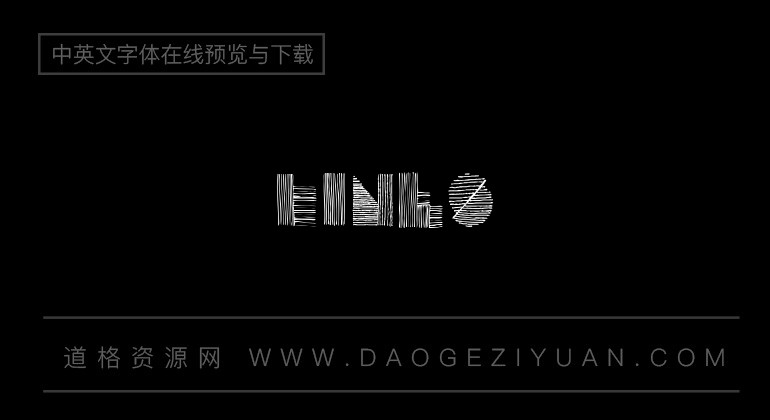
Lines
Lines 字体是一款简洁、现代的英文字体,由美国设计师 Brad Vetter 创作,于 2019 年发布。Lines 字体有着细腻的线条,外观清新自然,给人以温暖、柔和的感觉。它具有良好的可读性和辨识度,适用于标题、正文、标签等文字,是一款非常适合用于网页设计、平面设计、海报、书籍等的字体。
Lines是一款非常不错的手写艺术字体,具有很好的视觉感,适合于文化类的宣传设计、商业类品牌的广告和产品包装设计以及个性化文字排版等较多场景。